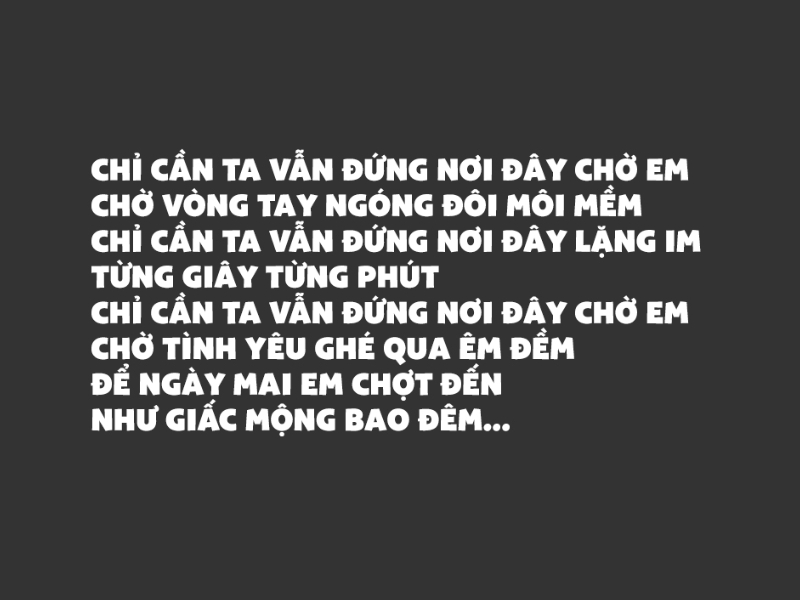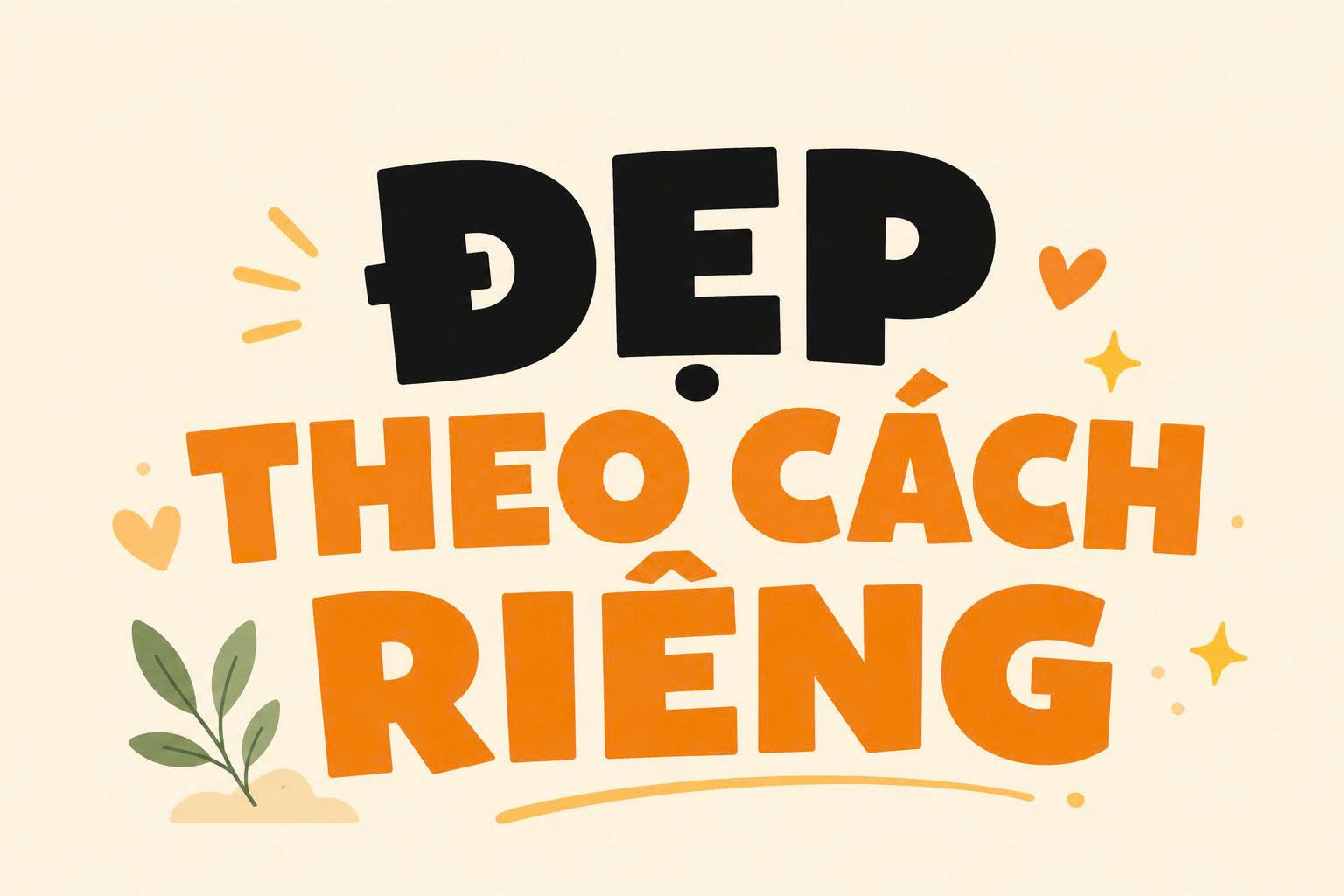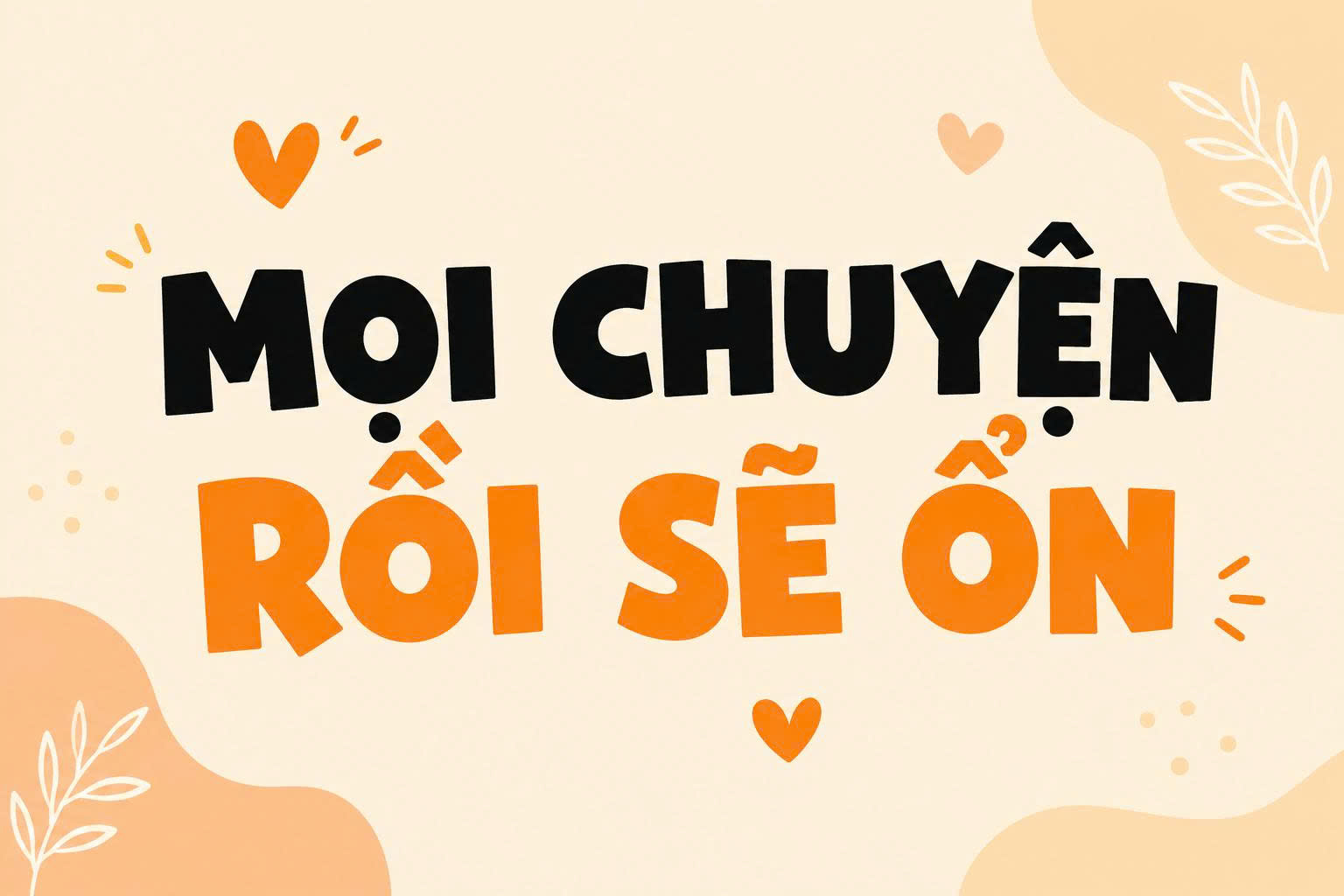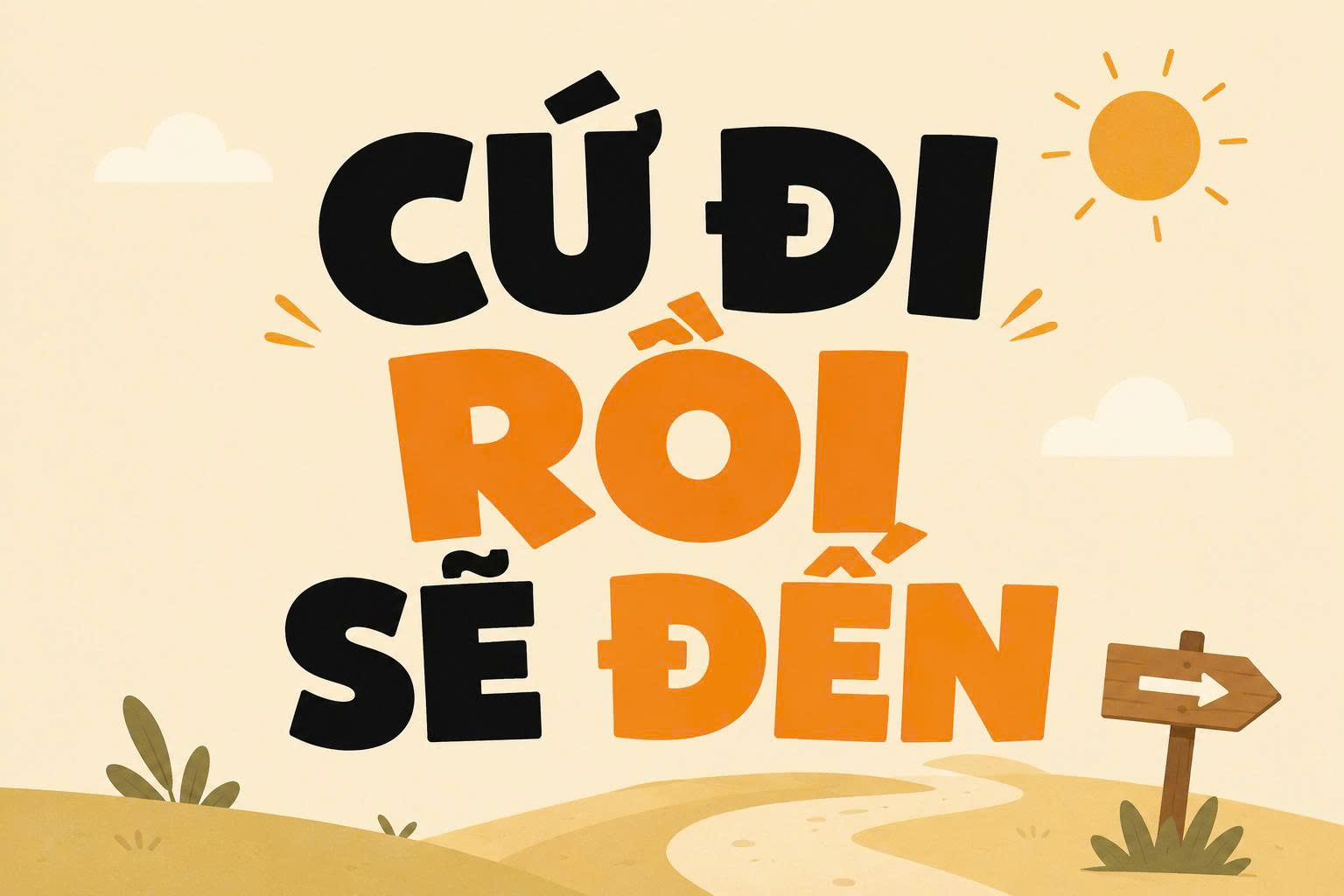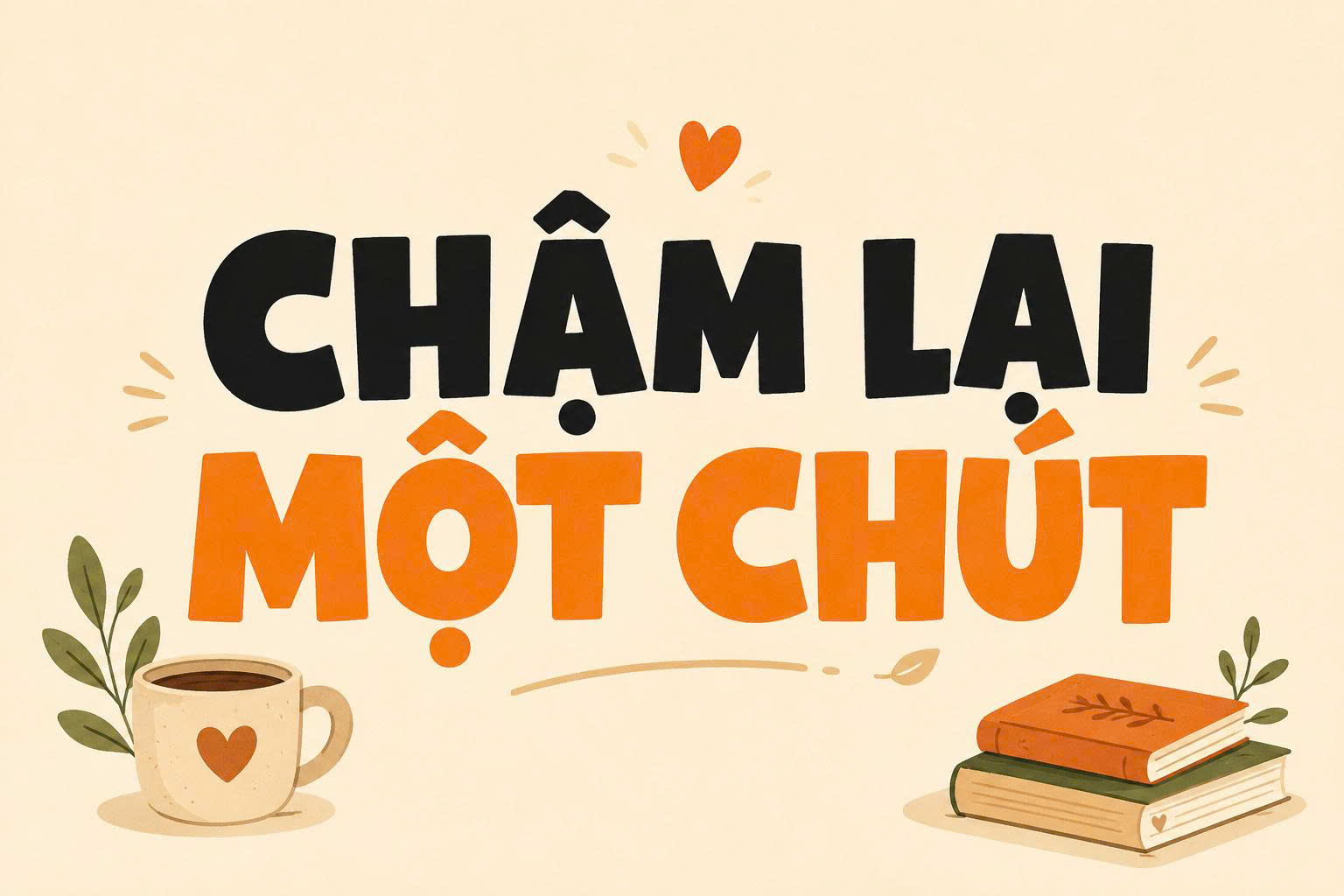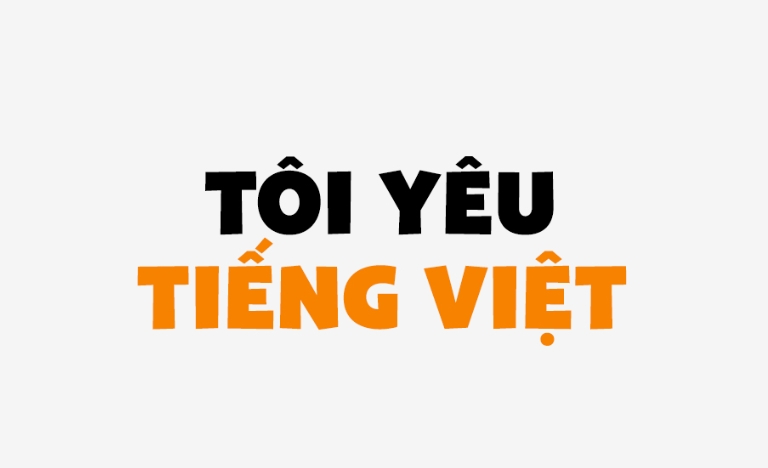
Font Việt hóa SVN Bango là một trong những bộ font thuộc phong cách display với những nét chữ dày, đậm và bo tròn đầy thân thiện. Đây là lựa chọn phù hợp cho những nhà thiết kế đang tìm kiếm sự nổi bật, vui nhộn nhưng vẫn giữ được sự chỉn chu và hiện đại trong bố cục.
Đặc trưng nổi bật của bộ font Việt hóa SVN Bango
Điểm thu hút của SVN Bango nằm ở độ nặng của các nét chữ (heavy weight) nhưng lại được kết hợp với các góc bo mềm mại, giúp giảm bớt sự thô cứng thường thấy ở các font chữ đậm. Bản font Việt hóa SVN Bango đã được tinh chỉnh hệ thống dấu tiếng Việt một cách tỉ mỉ, giúp các dấu thanh không bị chồng chéo hay làm biến dạng cấu trúc của ký tự gốc.
Bên cạnh đó, SVN Bango sở hữu khả năng hiển thị khá ổn định trên nhiều nền tảng khác nhau. Dù được sử dụng trên bản in bảng hiệu hay hiển thị trên màn hình kỹ thuật số, bộ font này vẫn giữ được độ rõ nét và sự cân đối. Điều này mang lại sự thuận tiện cho người dùng khi triển khai các dự án truyền thông đòi hỏi sự đồng nhất cao về mặt thị giác.
| Phong cách | Display, Bold, Rounded |
| Mục đích phù hợp | Tiêu đề, Poster, Logo, Bảng hiệu |
Gợi ý từ chuyên viên: Với đặc tính nét chữ rất dày, SVN Bango phát huy hiệu quả thị giác cao khi bạn sử dụng các tông màu rực rỡ hoặc tương phản mạnh. Bạn nên hạn chế dùng font này cho các đoạn văn bản dài để tránh cảm giác nặng nề cho người đọc.
03 Ứng dụng bango font việt hóa trong trang trí và quảng cáo
Với vẻ ngoài hiện đại và đầy năng lượng, bộ font chữ này mang lại giá trị thẩm mỹ cao khi được đưa vào thực tế xây dựng và quảng bá thương hiệu:
- Thiết kế bảng hiệu cho Homestay và Cafe: Những nét chữ tròn trịa của bango font việt hóa rất ăn ý khi xuất hiện trên các biển hiệu gỗ hoặc alu màu sắc. Đối với các dự án nhà lắp ghép dành cho giới trẻ, font chữ này giúp không gian trở nên trẻ trung và bắt mắt hơn.
- Trang trí không gian cho trẻ em: Bạn có thể dùng font Bango để làm decal dán tường, bảng tên phòng tại các khu vui chơi hoặc phòng ngủ trong các căn hộ hiện đại. Nét chữ đầy đặn tạo cảm giác an toàn và vui tươi, phù hợp với tâm lý trẻ nhỏ.
- Poster quảng bá dự án xây dựng: Sử dụng Bango cho các tiêu đề chính trên banner hoặc hồ sơ giới thiệu dự án nhà container sẽ giúp thông tin trở nên nổi bật, dễ dàng thu hút sự chú ý của khách hàng ngay từ cái nhìn đầu tiên.
03 Lưu ý khi sử dụng font Việt hóa SVN Bango trong thiết kế
Để khai thác tối đa vẻ đẹp của bộ font này mà không làm hỏng bố cục chung, bạn nên lưu tâm một số kinh nghiệm kỹ thuật sau:
- Kiểm soát khoảng cách giữa các chữ: Do các nét chữ của Bango rất dày, đôi khi chúng có thể dính vào nhau nếu bạn để khoảng cách quá hẹp. Hãy nới lỏng khoảng cách một chút để chữ được thông thoáng và dễ đọc hơn.
- Lựa chọn màu sắc tương phản: Font display dạng bold như Bango sẽ trông rõ nét hơn nếu được đặt trên một nền có độ tương phản rõ rệt. Tránh phối các màu quá gần tông vì dễ gây ra hiện tượng bết chữ khi in ấn hoặc hiển thị ở size nhỏ.
- Phối hợp font chữ hài hòa: SVN Bango đóng vai trò rất tốt như một điểm nhấn chính. Để tổng thể thiết kế chuyên nghiệp, bạn nên kết hợp nó với một font chữ không chân (Sans-serif) mảnh và đơn giản cho phần nội dung phụ.